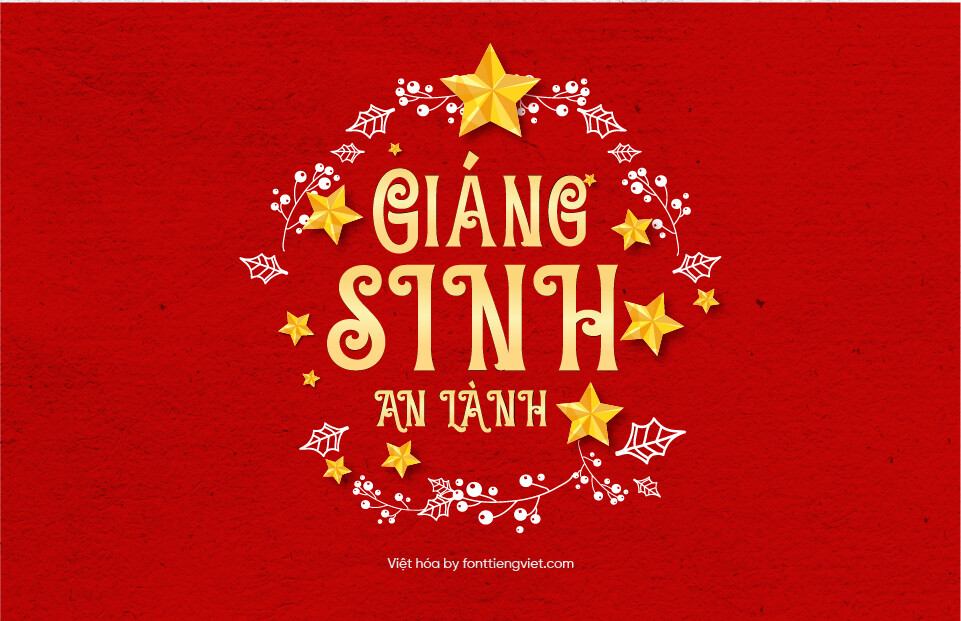
Font Việt hóa 1FTV VIP Christmas Beach – Giáng sinh cực đẹp cho thiết kế
Giới thiệu bộ Font Việt hóa 1FTV VIP Christmas Beach – Giáng sinh
Chào mừng bạn đến với bộ sưu tập phông chữ đặc biệt dành riêng cho mùa lễ hội năm nay. Font Việt hóa 1FTV VIP Christmas Beach – Giáng sinh là một sự kết hợp hoàn hảo giữa nét vẽ tay mềm mại và tinh thần phóng khoáng của những ngày nghỉ lễ trên bãi biển. Khi bạn tìm kiếm một Font Chữ mang đậm hơi thở hiện đại nhưng vẫn giữ được sự ấm áp, đây chính là lựa chọn không thể bỏ qua. Phông chữ này được tối ưu hóa hoàn toàn cho tiếng Việt, giúp các bạn học sinh và giáo viên dễ dàng tạo ra những ấn phẩm truyền thông đẹp mắt mà không lo lỗi font hay thiếu dấu. Với đường nét thanh mảnh và bay bổng, bộ font này mang đến cảm giác vui tươi, tràn đầy sức sống cho mọi bản thiết kế đồ họa.
Ưu điểm và ứng dụng của Font Việt hóa 1FTV VIP Christmas Beach – Giáng sinh
Đặc điểm nổi bật trong thiết kế
Ứng dụng thực tế trong trường học
Các bạn học sinh có thể sử dụng bộ font này để trang trí báo tường, làm thiệp chúc mừng gửi tặng thầy cô hoặc thiết kế slide thuyết trình sinh động. Trong môi trường học đường, sự sáng tạo luôn được khuyến khích và bộ font này sẽ là công cụ đắc lực giúp bài làm của các em trở nên nổi bật và chuyên nghiệp hơn rất nhiều.
Để tận dụng tối đa vẻ đẹp của bộ font, bạn nên kết hợp nó với những tông màu rực rỡ như đỏ, xanh lá hoặc vàng đồng. Hãy đảm bảo rằng khoảng cách giữa các chữ cái được điều chỉnh hợp lý để giữ được độ thanh thoát vốn có. Đây là một món quà tuyệt vời dành cho những ai yêu thích cái đẹp và sự sáng tạo. Chúc bạn có những tác phẩm thiết kế thật ấn tượng với Font Miễn Phí, Font Việt Hóa, Font Việt hóa 1FTV VIP Christmas Beach – Giáng sinh ngay hôm nay.